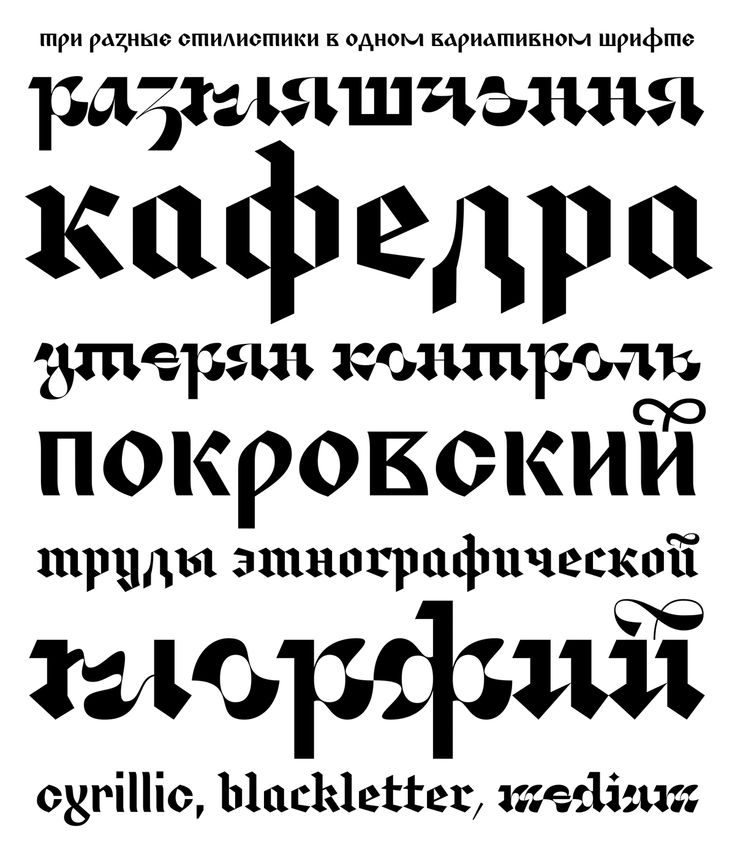
Кириллических шрифтов стало много, но их все еще в тысячи раз меньше, чем латинских. Решил подсказать дизайнерам, где кроме Google Fonts, найти отличные шрифты авторов, чувствующих кириллицу тонко и нативно. И, возможно, немного сэкономить.
Я начал изучать шрифт в 2002 году, и это было удивительное время: цифровые продукты для разработки шрифтов стали общедоступными, и больше не нужно было уезжать в Москву, чтобы устроиться в одну из крупных «словолитен». Начали появляться книги по типографике. Сфера только зарождалась, и все шрифтовые дизайнеры знали друг друга через 2–3 рукопожатия.
За 18 лет произошли грандиозные изменения. Во-первых, в профессию пришло огромное количество дизайнеров шрифта. Молодые и свободные, с современными инструментами и возможностью создавать шрифт самостоятельно.
Во времена СССР разрабатывать кириллицу можно было только в Москве. Повезло странам, которые пользовались латиницей: например, Литва, Латвия и Эстония могли создавать шрифты у себя дома. В Беларуси и Украине это было невозможно. Все изменилось, когда появились настольные издательские системы. Тогда отпала необходимость рисовать буквы на миллиметровках, задавать на приборах математические формулы и проверять начертание символов на осциллографе.
Беларусские дизайнеры
У нас по-прежнему два «постоянных» дизайнера и регулярные единичные проекты от еще нескольких. Самый продуктивный — Денис Серебряков.
Я считаю достойными внимания его следующие работы:
Самый первый дизайнер, проторивший шрифтовую дорогу в Беларуси — это я, Алексей Коваль. Первый шрифт на MyFonts я опубликовал в далеком 2008 году и тем самым застолбил себе финансовые условия получше: я получаю бóльший процент от продажи шрифтов, чем дизайнеры, которые заключили договор с сервисом несколько лет спустя.
Первая партия релизов пришлась на 2008–2012 гг. Затем я столкнулся с нехваткой знаний и начал изучать, почему шрифт сделан именно так.
Результат — мое возвращение в «большой шрифтовый спорт» в 2020 году. С тех пор у меня уже вышло три шрифта. Их можно купить на MyFonts: это мне вполне удобно. Некоторые шрифты я выпускаю в том числе и на физических носителях в сувенирном исполнении.
О теории и методике бренд-параметров шрифта
Skaryna 2017 Title. Красив в небольшом размере, как и оригинальный шрифт.
Очень нравится ритм в Caliady.
Кто еще из беларусских дизайнеров интересен
Хочу отметить шрифт Кати Бушук: живой, нетривиальный.
В нем каждая буква уже сама по себе красавица, но каким-то чудом еще умудряется работать вкупе с остальными.
Шрифт «Берегиня» Михаила Боярина. Очень круто, когда шрифтовая технология используется для нетривиальных задач. Орнамент, в который преобразуется текст, с одной стороны, убедителен, с другой — может быть прочитан даже поисковиком.
Украинские дизайнеры
Украинский шрифтовой рынок развит лучше, чем белорусский. Это связано с тем, что там существует активное шрифтовое сообщество: носители традиций, профессионалы и студенты передают друг другу знания и применяют их на практике.
Для современных украинских шрифтов характерно каллиграфическое влияние. Возможно, потому что во времена СССР украинцы, так же как и беларусы, не могли разрабатывать шрифт у себя в стране, но могли заниматься оформлением.
Вообще в любой сфере важно, чтобы эти 3 поколения общались. Носители традиций передают знания; профессионалы, которые зарабатывают на жизнь своим ремеслом, делятся актуальной информацией; а студенты все это впитывают и вырастают в новых профессионалов или носителей традиций. Так вокруг профессии формируется сообщество.
Шрифт Kyiv Type Дмитрия Растворцева опирается на исторические формы, не создавая при этом ощущение архаичности.
Восхищаюсь шрифтами от мэтров. Например, «Арсеналом» Андрея Шевченко.
Многое для развития шрифтовой культуры в Украине делает
Шрифтовые бутики в Украине
Альфа Браво
Проект Кирилла Ткачева, который многое делает для развития шрифтовой культуры в Украине.
Помимо управления словолитней АльфаБраво, Кирилл организовывает фестиваль «Простор литер» и является автором отличных практических курсов по дизайну шрифтов. Его персональные работы мне нравятся живостью даже в гротескной форме.
RentaFont
На этом сервисе шрифт можно арендовать на время от нескольких минут до недель. Стоимость получается копеечная. Это удобно, когда шрифт нужен для одного клиента. Часто нет резона покупать десктоп-лицензию, а рациональнее приобрести кратковременную.
Право на участие
Современная кириллица открыта для всех. На участников не распространяются какие-либо ограничения по возрасту, образованию, роду занятий или владению языками, использующими кириллицу. Количество записей не ограничено. Участвовать могут как физические, так и юридические лица.